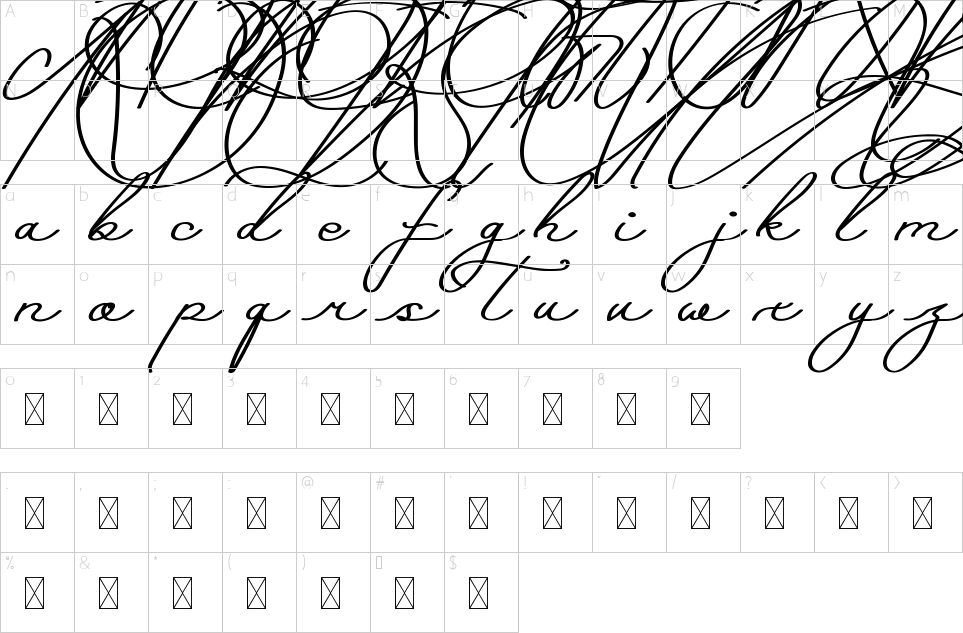
A fonte Paradisy, disponível gratuitamente para Windows e Mac, foi criada pelo designer nihstudio. Com um design elegante e moderno, Paradisy é uma excelente escolha para aqueles buscando uma fonte clássica com um toque de originalidade. Esta fonte tem se destacado na comunidade de designers graças à sua facilidade de utilização e variedade de aplicações. Recentemente, mais de 2.500 pessoas já utilizaram esta fonte, evidenciando sua popularidade e qualidade. Seja para criar logotipos, design de websites ou até mesmo para escrita de textos, Paradisy oferece um toque único e sofisticado. Compre agora sua própria cópia da fonte Paradisy e adicione um toque especial a suas criações.